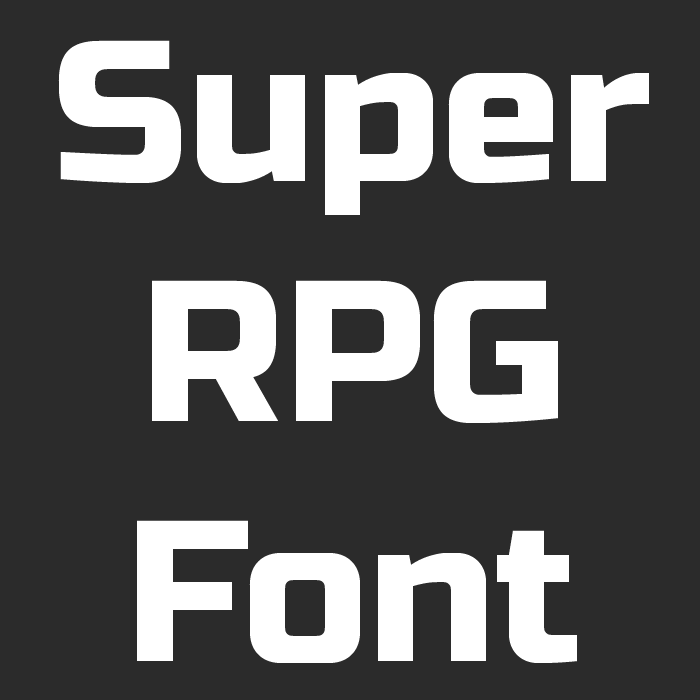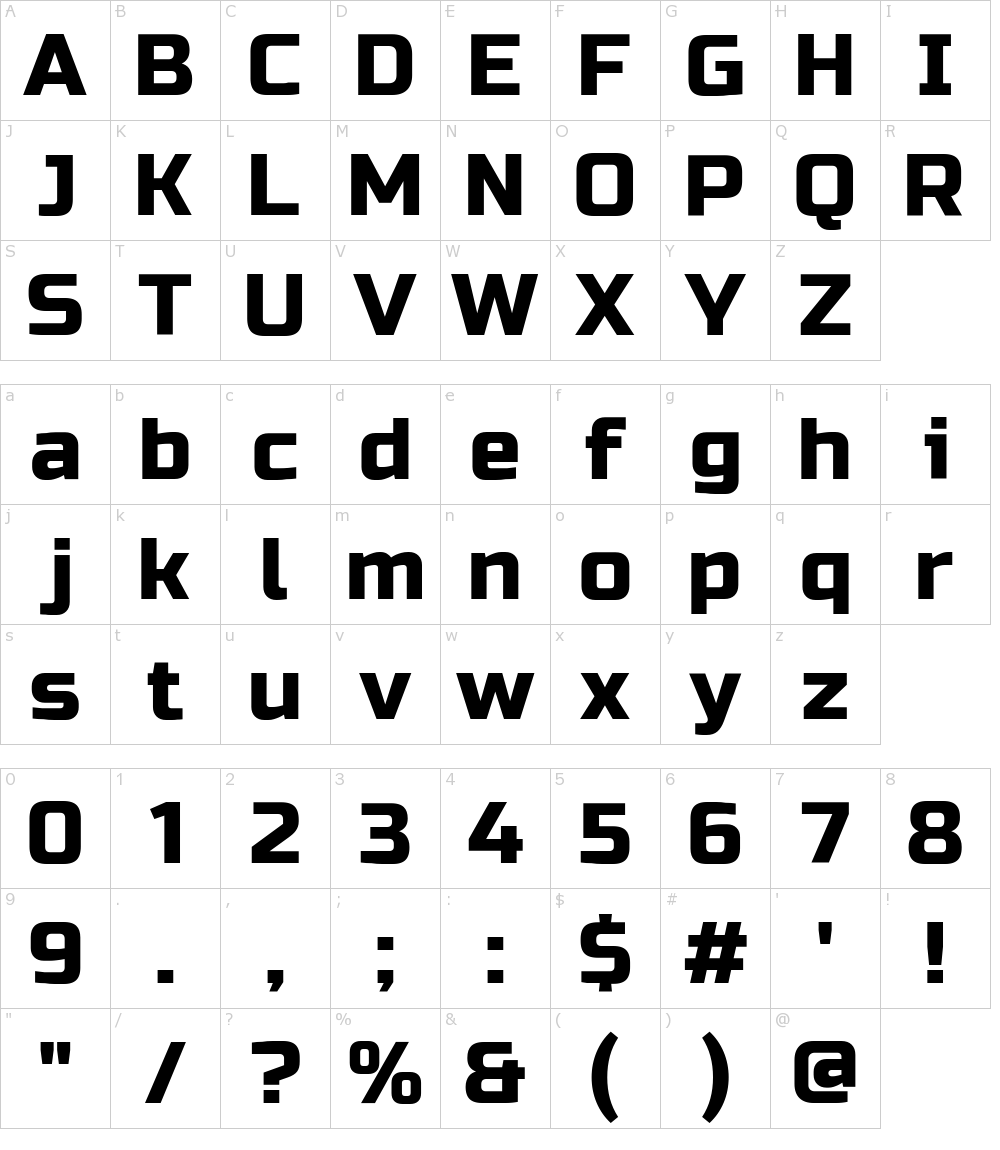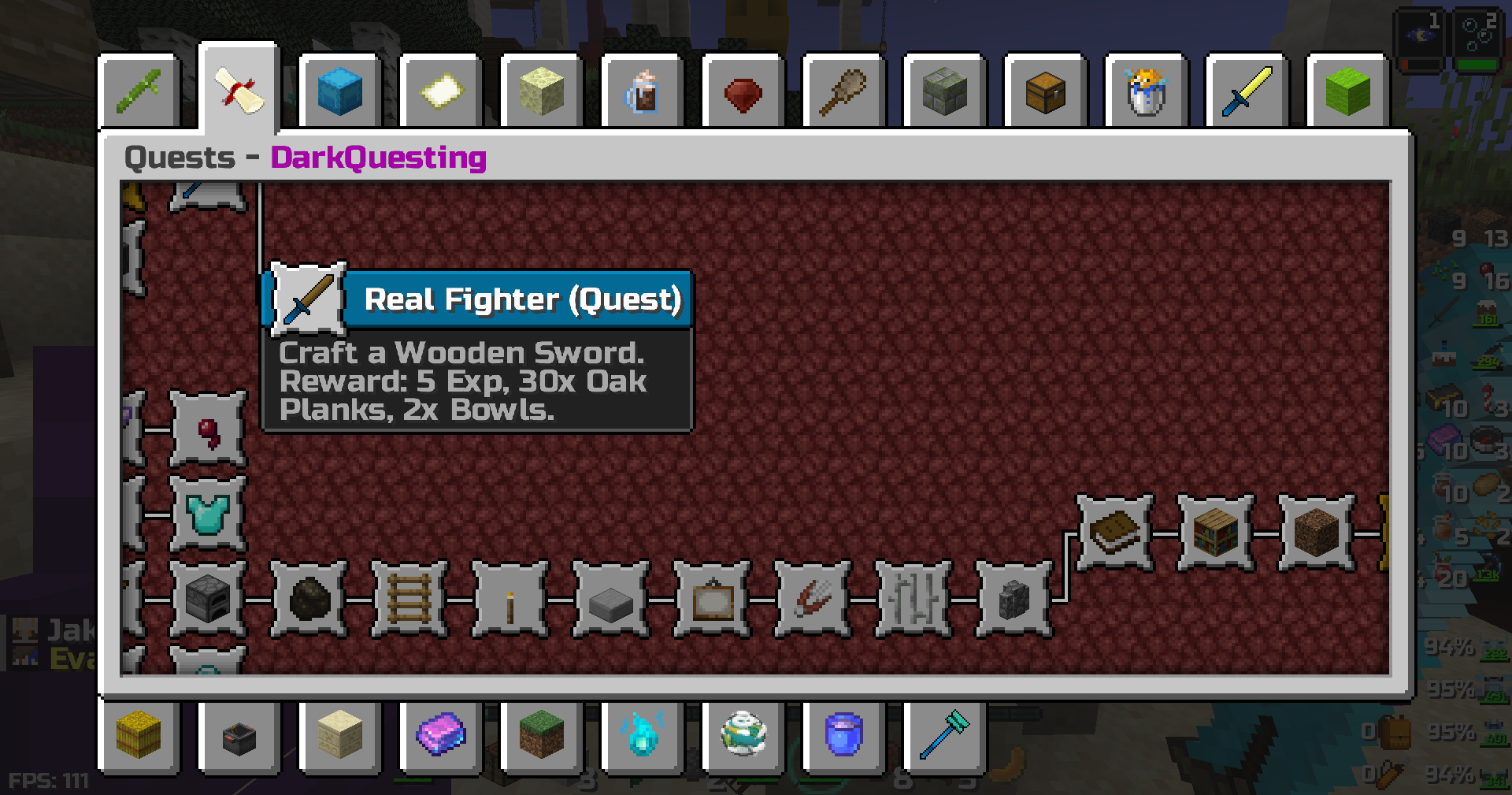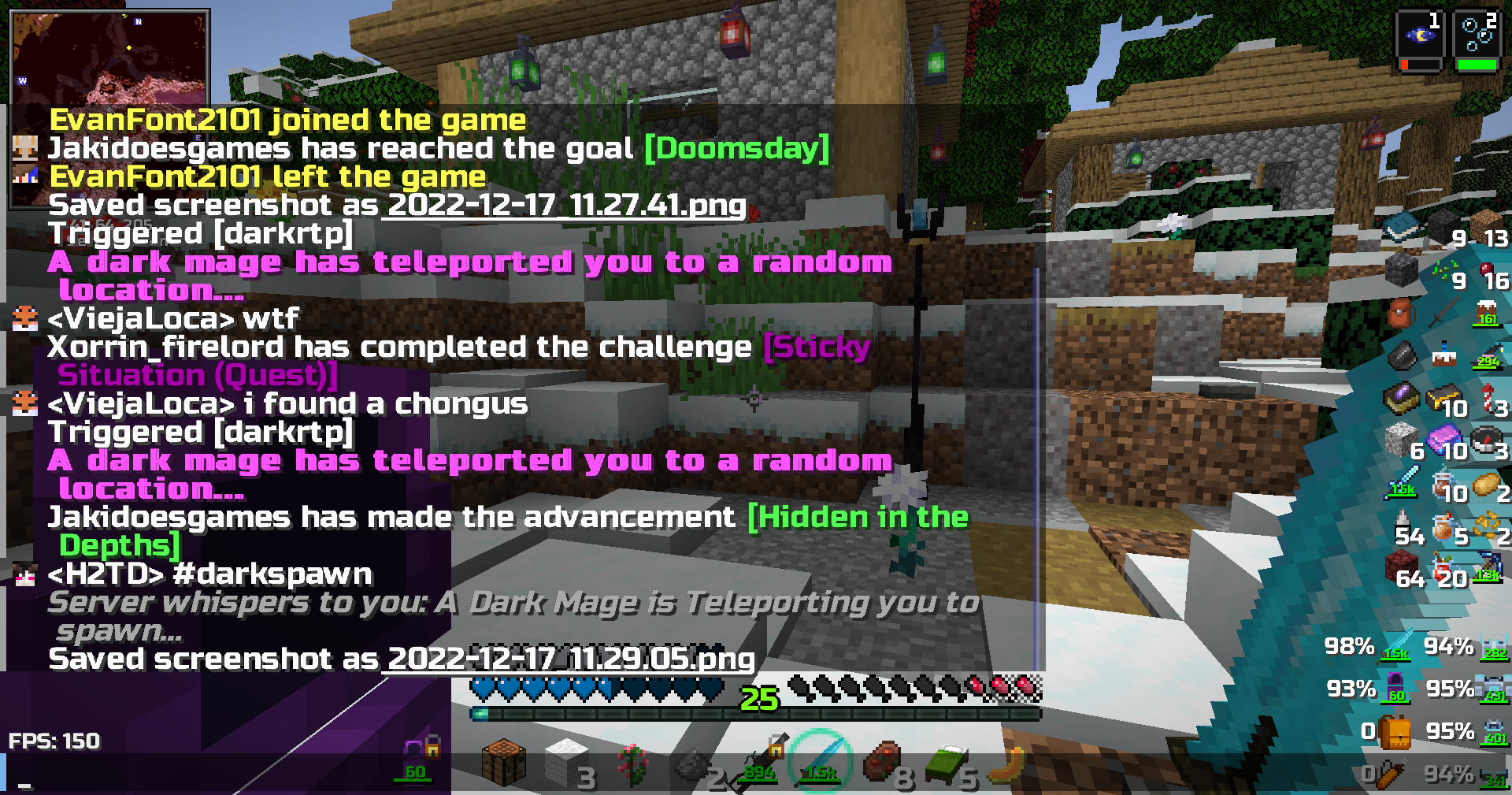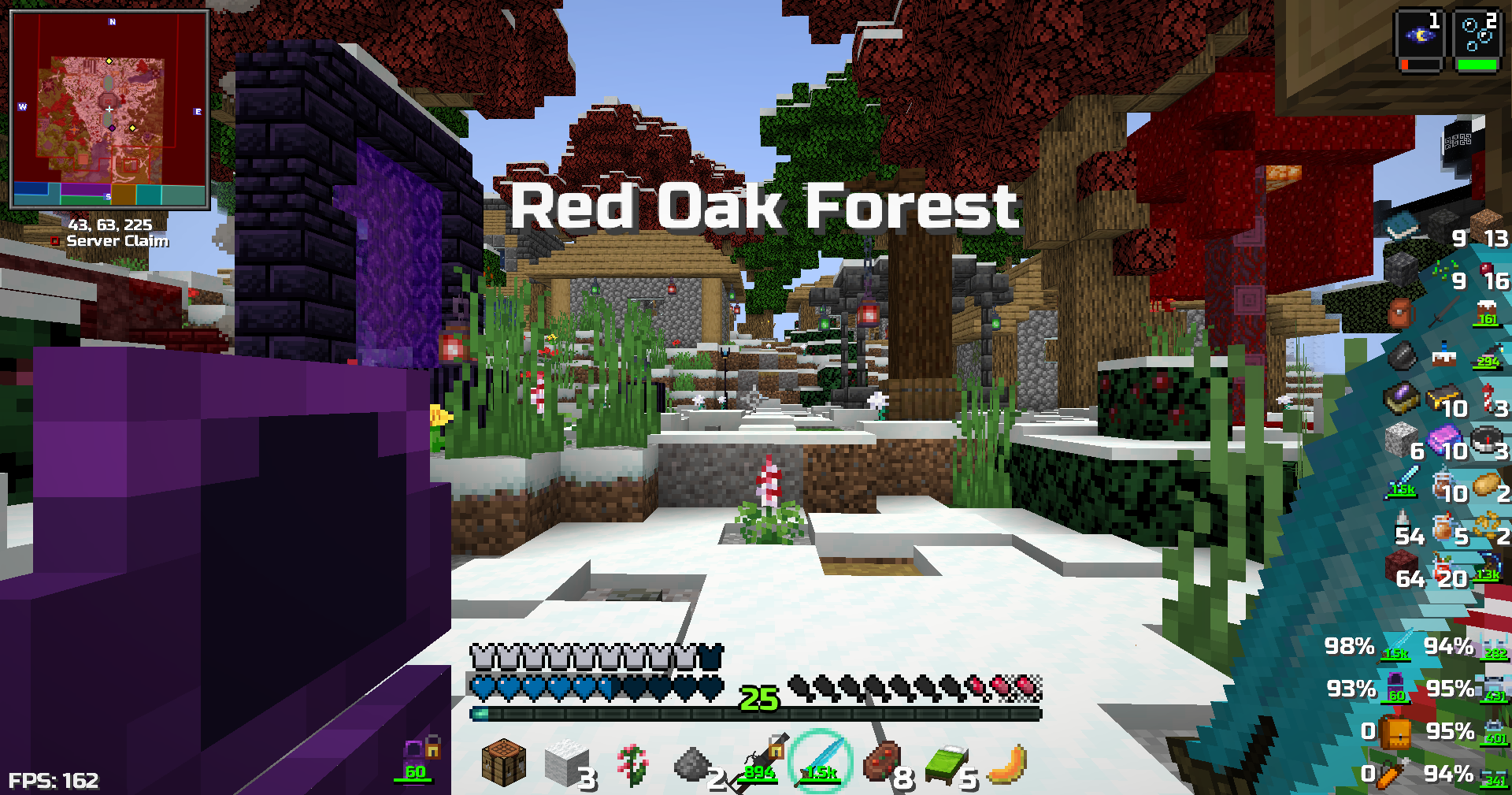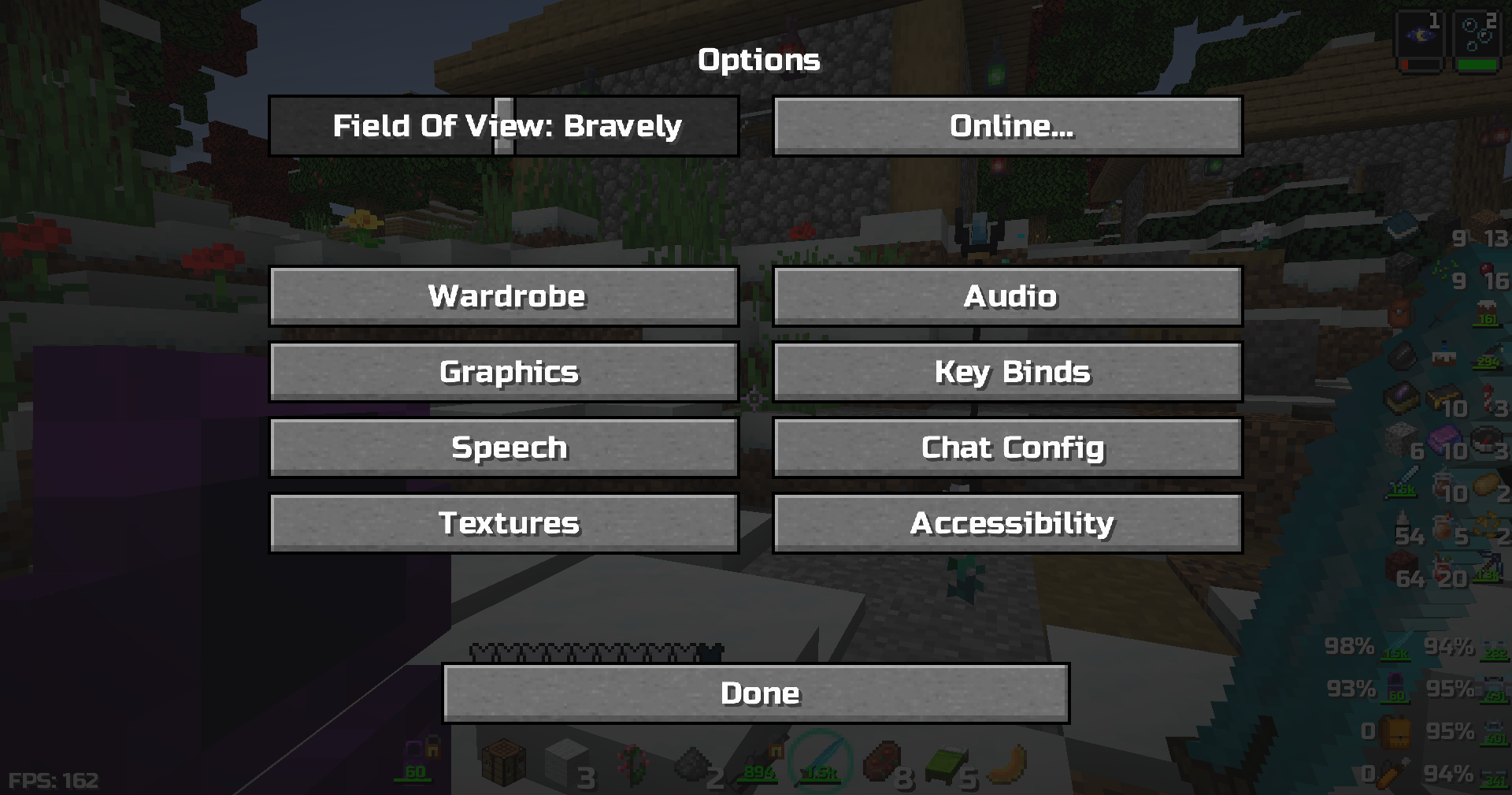
Super RPG Font: Улучшенный шрифт для вашего Minecraft
Если вы любите RPG-стиль в Minecraft и хотите, чтобы текст в игре выглядел более атмосферно, Super RPG Font — отличное решение. Этот шрифт придаст вашему миру уникальный вид, сделав интерфейс более читаемым и стильным.
🔍 Что такое Super RPG Font?
Это модифицированный шрифт для Minecraft, созданный для улучшения визуального восприятия текста в игре. Он основан на популярном Russo One от Google Fonts и идеально подходит для:
- RPG-модов и модпаков (например, DarkRPG)
- Серверов с тематикой фэнтези
- Игроков, которые хотят изменить стандартный шрифт
📌 Основные особенности:
✔ Четкий и удобочитаемый стиль
✔ Поддержка кириллицы (важно для русскоязычных игроков)
✔ Разрешение 32x для лучшей детализации
✔ Совместимость с большинством версий Minecraft
🎮 Где лучше всего использовать этот шрифт?
Super RPG Font отлично сочетается с:
- Модпаками в стиле RPG (DarkRPG, RLCraft)
- Серверами с глубоким лором (например, Medieval MC)
- Кастомными интерфейсами (HUD-моды, квестовые системы)
Если вы играете на сервере, такой шрифт добавит атмосферности и сделает взаимодействие с чатом и меню более приятным.
🔥 Заключение
Super RPG Font — это небольшое, но важное улучшение для тех, кто хочет сделать свой Minecraft более стильным. Простая установка, отличная читаемость и поддержка кириллицы делают его отличным выбором для русскоязычных игроков.